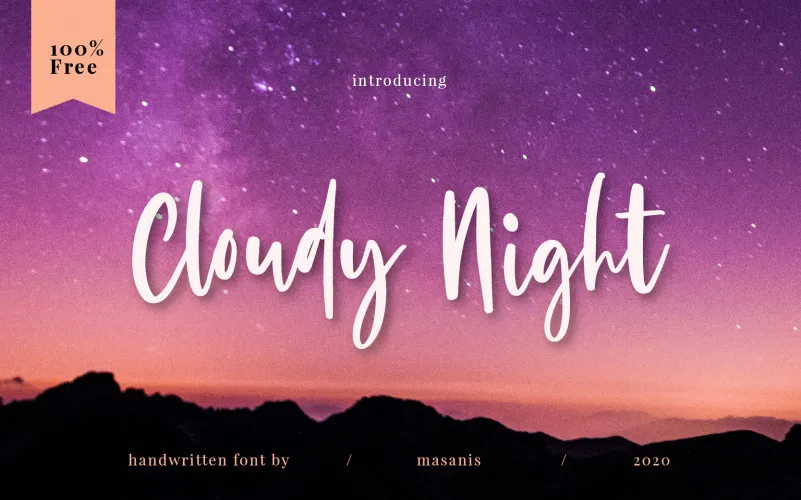
Cloudy Night Script Font – Download Grátis
Descubra a beleza natural e sofisticada de Cloudy Night Font, uma linda nova adição à nossa seleção de Script Fonts. Inspirada no lifestyle casual que valoriza a simplicidade e a elegância, esta fonte é perfeita para quem procura um touch especial em seus designs. Ideal tanto para editoriais detalhadas quanto para gráficos chamativos, Cloudy Night oferece uma textura única que parece fluir naturalmente. Perfeito para nomes de publicações, títulos cinematográficos ou livros, indicações de casamento, menus de restaurantes, e até mesmo estampas de camisetas. Para designers de foto ou editoriais de moda, o Cloudy Night é perfeito para incorporar um toque diferente em suas criações. Também serve bem como fonte para flyers, panfletos, banners publicitários, design web e impressão. Cloudy Night é uma opção versátil que vai muito além das simples ilustrações; está disponível para todos aqueles que estão procurando dar um toque especial em seus trabalhos. Seja você um designer profissional ou alguém que adora criar suas próprias ideias, esta fonte pode trazer uma nova dimensão ao seu trabalho.